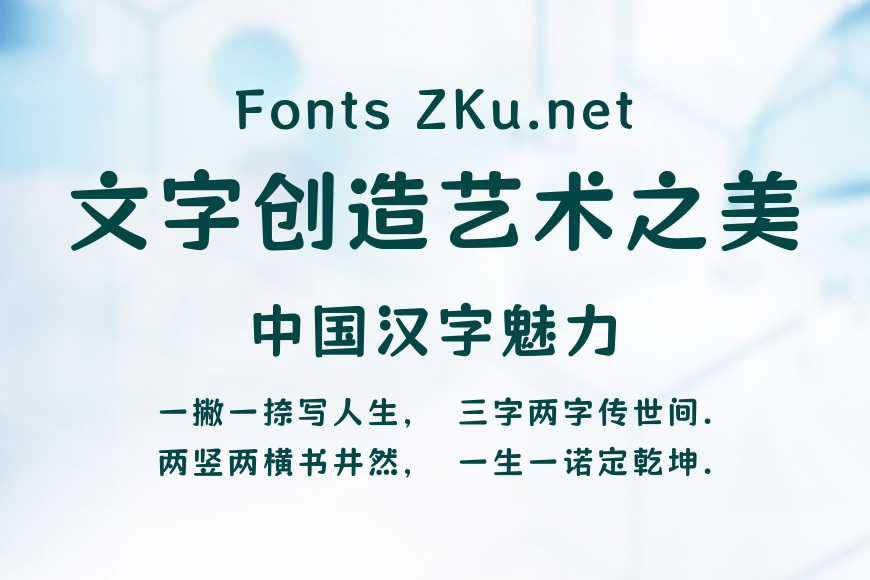
猫啃珠圆体 详情页
字体名称: 猫啃珠圆体
猫啃珠圆体
猫啃珠圆体介绍
在2023年初,猫啃网携手标小智用心打造了一款卡通字体【标小智龙珠体】,字体风格动感活泼俏皮可爱,非常适合用在卡通类logo设计中,广受大家的喜爱。
后来发现把龙珠体的笔划调整成圆润的风格,看上去效果也非常可爱,别有一番风味,十分适用于儿童,母婴产品以及萌系动画等场合,为此类场景增添天真可爱,无拘无束,自由自在的活力。这款字体除了用作标题,用于正文字体也有一种萌萌的感觉。
于是@Little White Dog对字体整体进行笔划弧度的调整,@频凡兄对字体进行细节上的调整,主要调整转折上部,而比较窄小部分则保持原有的转角,使字体效果看上去更和谐。最后把字体命名为猫啃珠圆体分享给大家使用,请大家尽情享用吧!